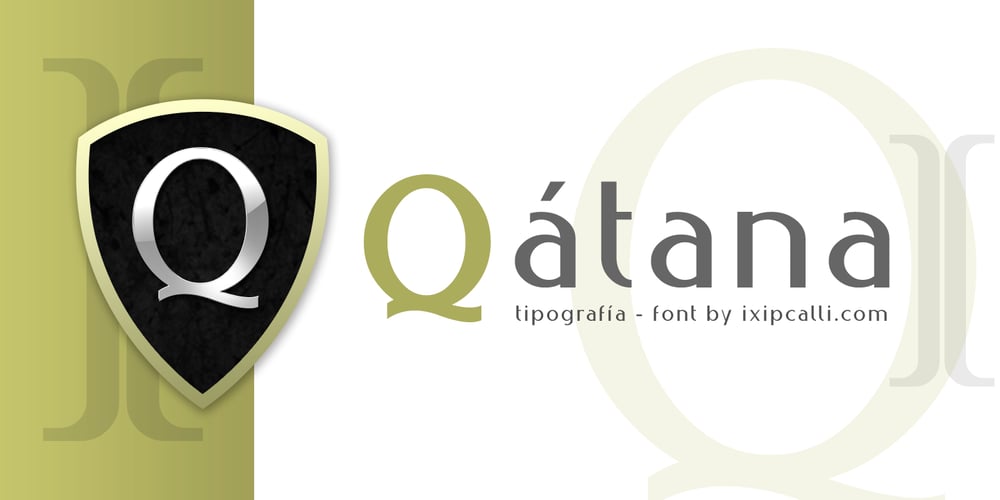
Qatana
Qatana font
Qatana Font Family was designed by Francisco Arellano and published by Ixipcalli. Qatana contains 6 styles and family package options. La tipografía Qátana es una tipografía inspirada en el estilo románico serif y sans serif. Su estilo elegante y de fácil lectura ha logrado ser una tipografía esencial para redacciones de documentos, textos o libros. Cuenta con tres pesos bien marcados que dan un juego visual de resaltados y tenues. Además de las formas itálicas.The Qátana typeface is a typeface inspired by the Romanesque serif and sans serif style. Its elegant and easy-to-read style has become an essential typeface for writing documents, texts, or books. It features three well-marked weights that give a visual play of highlights and lows. In addition to the italic forms.